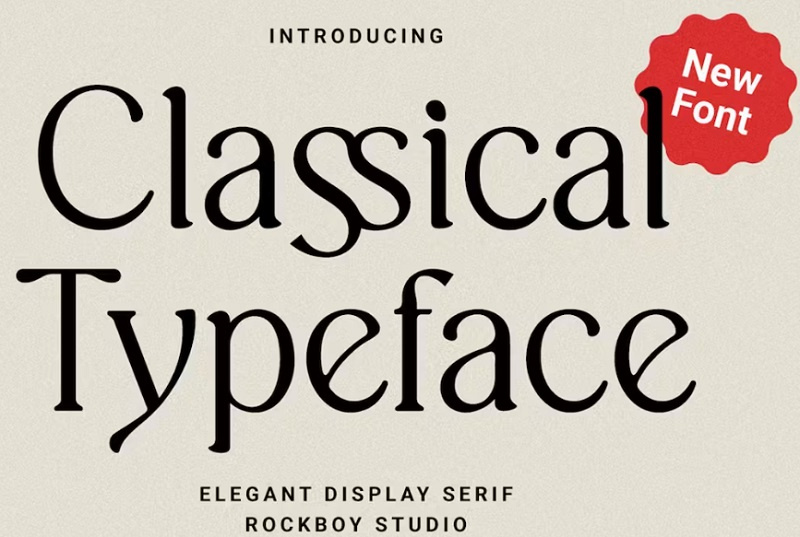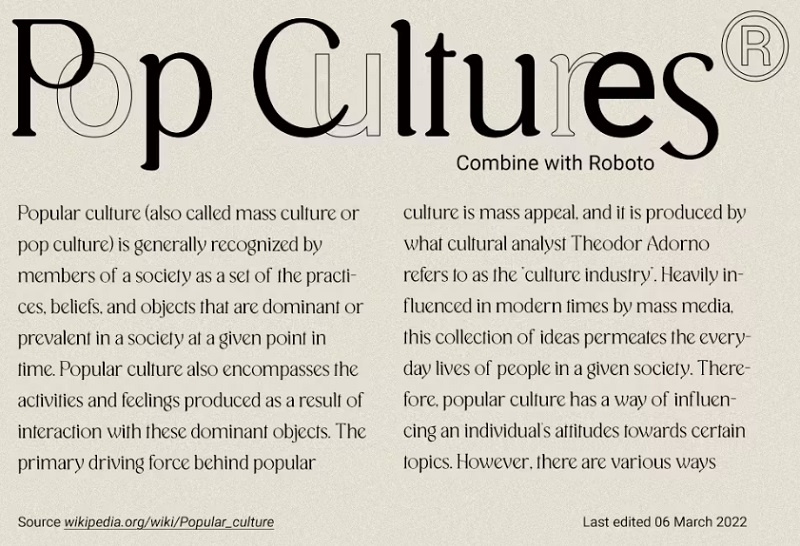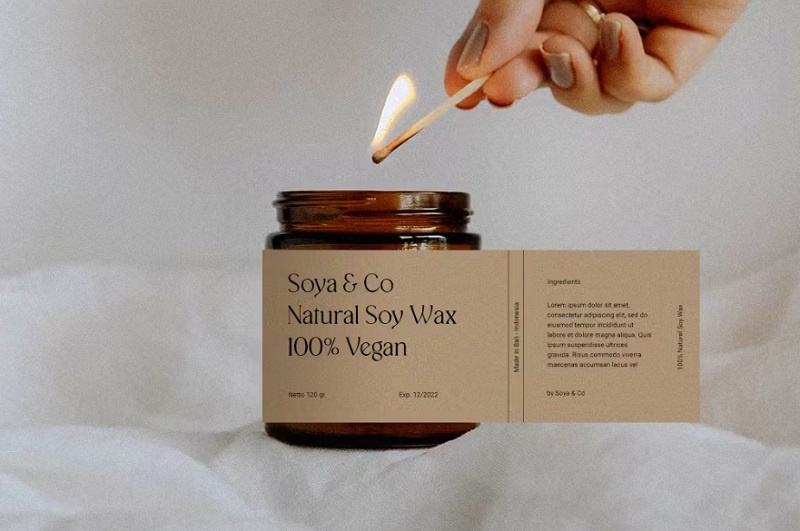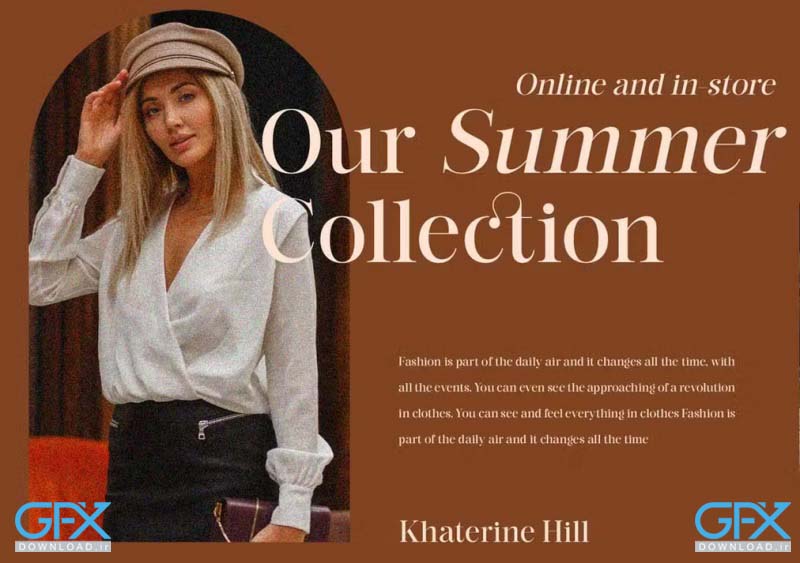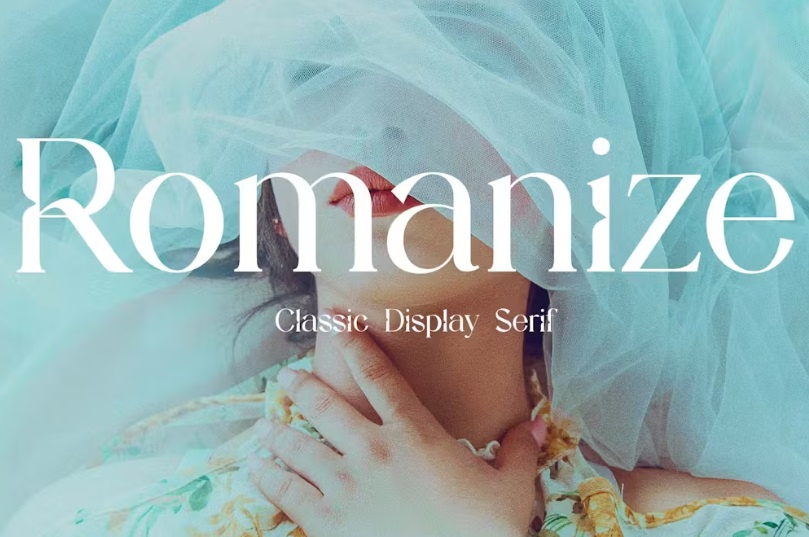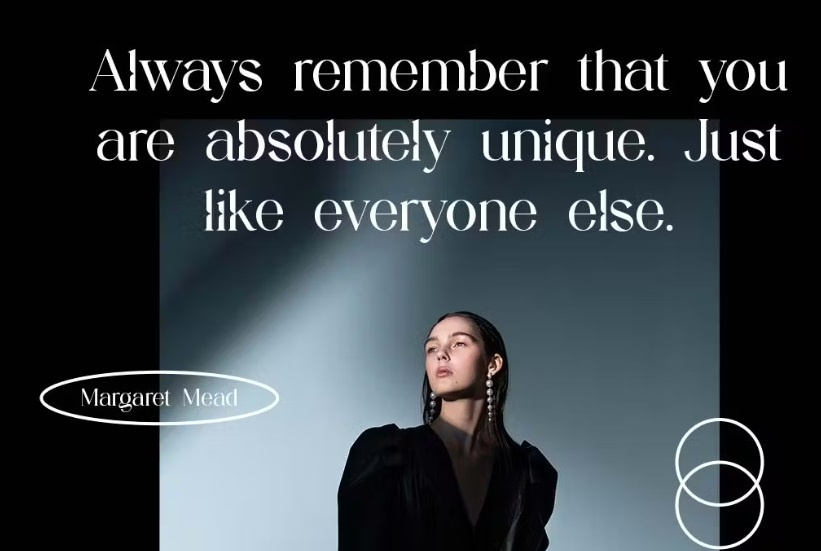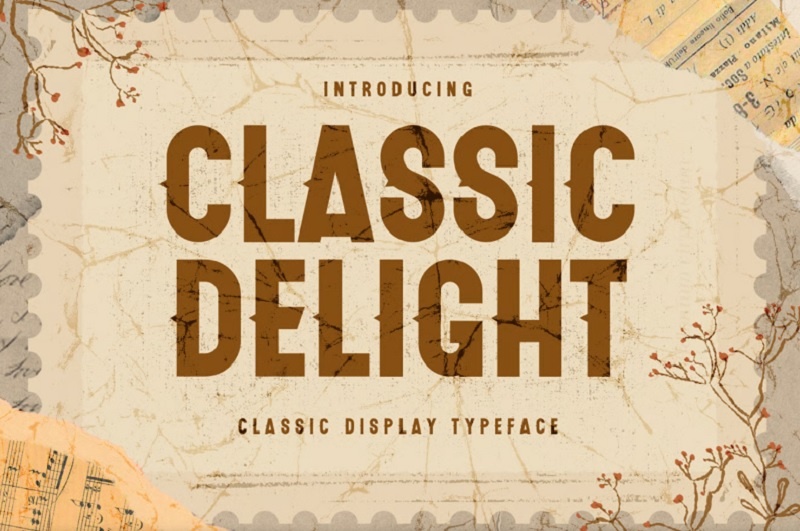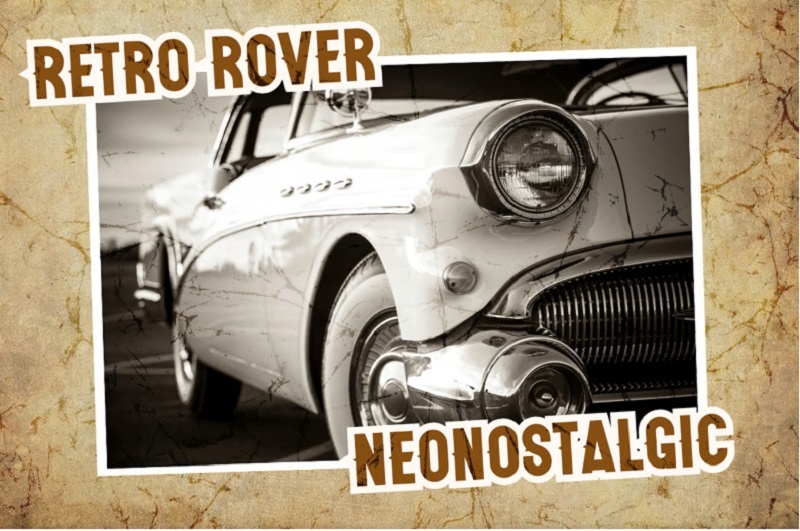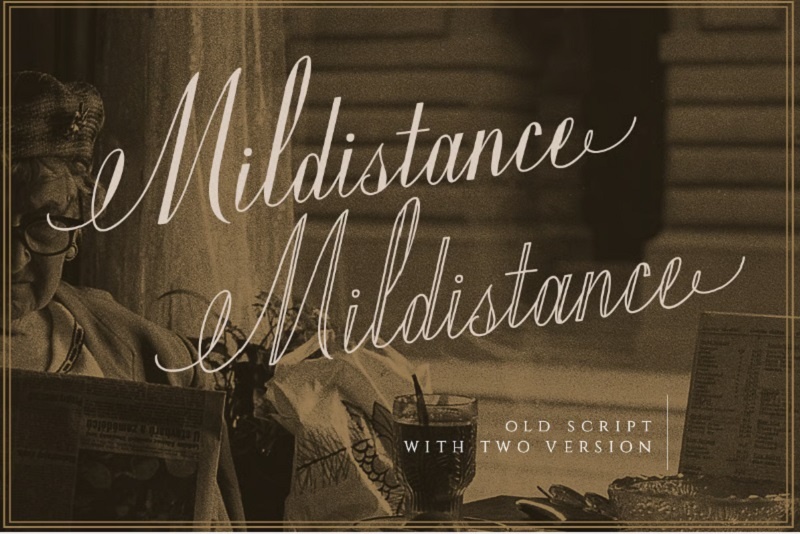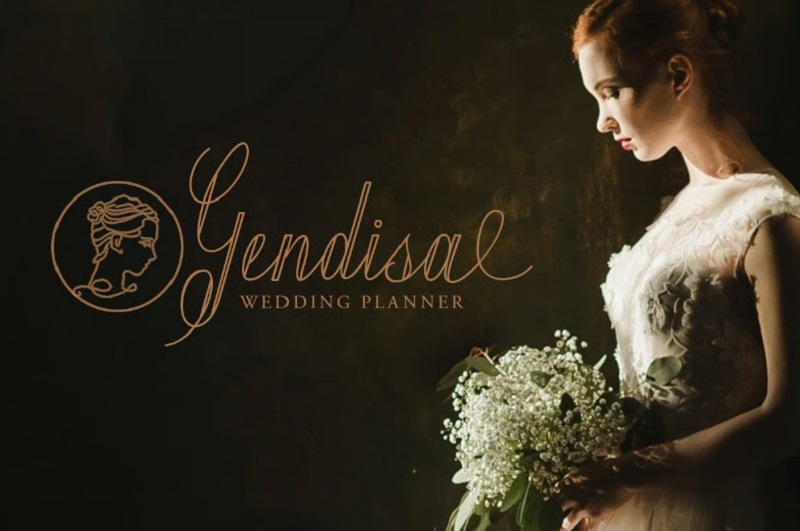
فونت انگلیسی کلاسیک شامل بهترین فونت های کلاسیک آنلاین
مجموعه بهترین فونت های انگلیسی کلاسیک در جی اف ایکس دانلود. در این مطلب سعی کرده ایم برای شما جدیدترین و پرکاربردترین فونت های کلاسیک انگلیسی را قرار دهیم. شما می توانید از فونت های انگلیسی کلاسیک برای طراحی های مختلف استفاده نمایید، طراحی های لوگو تایپوگرافی، جلد محصولات، ساخت کاتالوگ، تراکت، بروشور و...تنها چندین کاربرد استفاده از فونت های کلاسیک می باشد. برای مشاهده ویژگی های کامل این مجموعه فونت انگلیسی و دریافت فایل ها به ادامه مطلب مراجعه نمایید.
اگر به دنبال راهی هستید تا اسناد، دعوت‌نامه‌ها یا هر نوشته‌ای که دارید را به یک اثر هنری تبدیل کنید، فونت انگلیسی کلاسیک می‌تواند همان جادوی پنهانی باشد که به دنبالش هستید! تصور کنید که با یک نگاه به متن نوشتاری‌تان، حس قدم زدن در کوچه‌های تاریخ و لمس اصالت و زیبایی فرهنگ‌های گذشته را تجربه کنید. این نوع فونت با خطوط زیبا و منحنی‌های دل‌نشین خود، نه تنها توجه بیننده را جلب می‌کند، بلکه با اصالت و شکوه خود، حس اعتماد و احترام را نیز منتقل می‌نماید. اگر می‌خواهید نوشته‌هایتان در میان انبوهی از متون بی‌روح و ساده بدرخشد و متفاوت باشد، انتخاب این مجموعه فونت می‌تواند به شما کمک کند تا به هدفتان برسید. اکنون بهترین زمان برای تجربه این حس ناب و شگفت‌انگیز است. با انتخاب پک فونت انگلیسی کلاسیک جی اف ایکس دانلود، نوشته‌های شما نه تنها زیبا، بلکه الهام‌بخش و به یاد ماندنی خواهند بود. پس فرصت را از دست ندهید و با این انتخاب هوشمندانه، امضای شخصی خود را به دنیای نوشتاری‌تان اضافه کنید!
1- دانلود فونت انگلیسی کلاسیک Janchuk
فونت انگلیسی کلاسیک Janchuk مناسب استفاده در اینشات و موبایل نیز می باشد.شما می توانید از فونت انگلیسی کلاسیک برای پروژه هایی مانند لوگو تایپوگرافی ، پوستر ، طراحی لباس ، برچسب و موارد دیگر استفاده نمایید.
2- دانلود فونت انگلیسی قدیمی و کلاسیک The Roots
THE ROOTS یک فونت انگلیسی قدیمی و دست ساز به سبک کلاسیک است که می توانید در جی اف ایکس دانلود این فونت را دریافت کنید. این فونت انگلیسی از برند تجاری قدیمی و صنایع دستی الهام گرفته شده است . دانلود فونت کلاسیک The Roots دارای فاصله ای زیبا بین هر کاراکتر ، همه حروف ، کاراکتر های متناوب و پشتیبانی از چند زبانه است. قابل استفاده برای لوگو ، لوگو تایپ ، عنوان ، بنر ، عنوان و علامت کلمات .
3- دانلود فونت کلاسیک Highpro در جی اف ایکس دانلود
دانلود فونت کلاسیک Glorich
4- دانلود فونت انگلیسی کلاسیک Glorich آپدیت اسفند 1401
یک فونت زیبا به سبک کلاسیک و مدرن با لیگاتور و جایگزین است! نکته خاص دیگر در مورد این فونت برای الفبای خاص است که می توانید بین حروف بزرگ و کوچک تفاوت کمی پیدا کنید! این فونت انگلیسی کلاسیک Glorich در هر پروژه و طراحی مناسب است. می‌توانید از آن برای عنوان، لوگو ، نقل‌قول یا جفت شدن با هر فونتی استفاده کنید. با این فونت هرگز اشتباه نخواهید کرد. این فونت از چند زبان نیز پشتیبانی می کند! این مطلب آپدیت خواهد شد.
دانلود فونت کلاسیک عاشقانه Classical Romance
5- فونت کلاسیک عاشقانه Classical Romance آپدیت خرداد 1402
دانلود فونت Classical Romance از سری فونت های کلاسیک با حس کلاسیک منحصر به فرد و عاشقانه و در عین حال مدرن! از جی اف ایکس دانلود. این فونت حروف ظاهری کمی خشن دارد و به صورت کلاسیک و عاشقانه متن های شما را به نمایش در می آورد. شما می توانید از این فونت برای طراحی لوگوها، برندها، پوشاک، طراحی پوستر، مجله آنلاین، خودرو و موارد دیگر استفاده کنید. این فونت به صورت آپدیت به مطلب اضافه شده است، شما با خرید این مجموعه می توانید به تمامی فونت های سبک کلاسیک دسترسی داشته باشید.